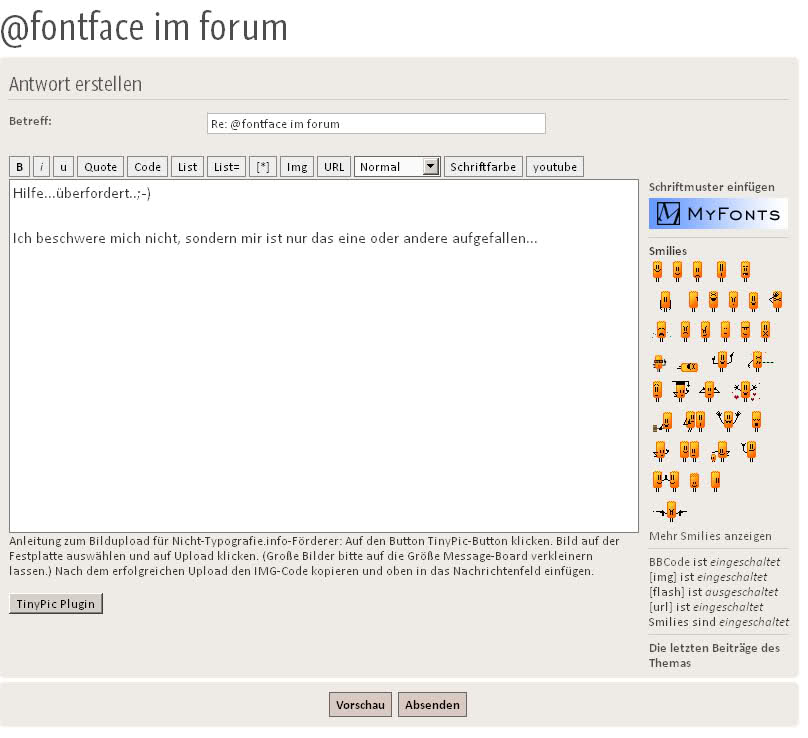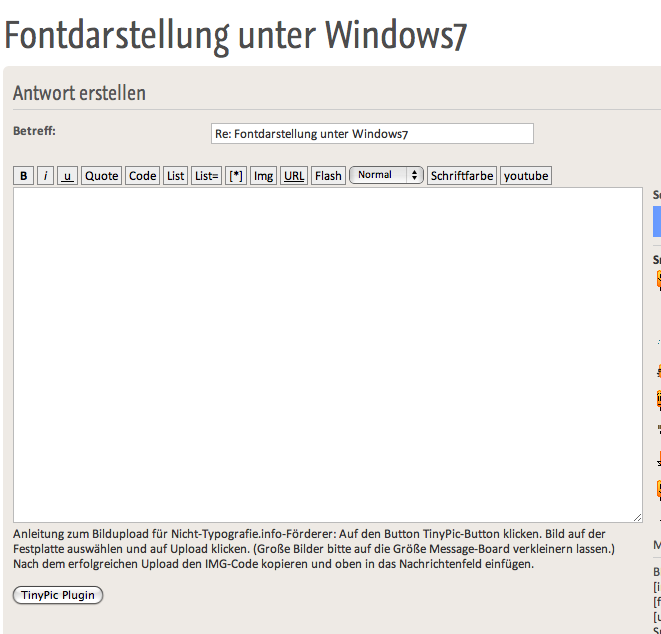
Fontdarstellung unter Windows7
Abgetrennte Diskussion von "@font-face im Forum"
Wenn ich meine unwissentliche Meinung abgeben dürfte (aber nicht hauen..;-) )
Das Problem der Darstellung ist mir auch schon aufgefallen, besonders im Eingabe-Editor.
Das ganze sieht aus wie bei Win7 mit eingeschaltetem ClearType (welches dort noch schlimmer ist als unter XP) und was auch der Grund für mich war, Win 7 erst mal nicht zu benutzen, da mir das Lesen mit solchen Buchstaben auf die Dauer zu anstrengend ist (ich merke wirklich dabei einen Unterschied zwischen XP und Win 7).
Da frage ich mich doch gleich, warum das als solch eine Errungenschafft angesehen wird, wenn sich eine Menge User im Netz darüber beschweren?
Was ich damit sagen will: Wenn jemand Win 7 hat, darf er sich nicht darüber wundern, dass die Schrift so ausschaut - nur ohne ClearType sieht es nur noch pixelig aus - warum gibt es nicht wie bei XP die Funktion "normal"?
Btw: Eine andere Frage, wo ich gerade die Fachleite hier habe: Ich weiß dass die Frage fast eienr Blasphemie gleich kommt, aber benutzt zufällig jemand heir Win 7 in Verbindung mit Photoshop, Illustrator und anderen Programmen und kann mir sagen wir ob die Schrift in den Programmen genauso ausschaut wie von Win 7 selber? Also genau so unscharf an den Rändern?
Hilfe...überfordert..;-)
Ich beschwere mich nicht, sondern mir ist nur das eine oder andere aufgefallen...
So schaut das ganze bei mir unter Win XP und FF aus:
Was ich jetz nur sagen woltle ist, dass Win 7 die Schrift generell schlchte darstellt (sieht man auch im FF):
Win XP:
Win 7:
Nicht das jemand denkt, wir schlecht die Schrift hier an manchen Stellen ist, und es liegt doch an Win 7...
Möglich, dass die Cleartype-Standardmethode von XP mit deinem Display besser funktioniert hat als die von Win7 - deine Screenshots deuten darauf hin. Cleartype-Tuner hilft.
Darstellung von Schrift in Photoshop, Illustrator, Indesign, ...: nein, diese Programme stellen Schrift auf ihre Weise mit einer eigenen Rasterungsmethode dar - möglichst Print-nahe, während das System die Schriften möglichst Bildschirm-optimiert darstellt (so der Microsoft-Ansatz).
Dann schmeiß mal den ClearType Tuner an – das sieht wirklich gruselig aus und hat mit dem eigentlichen Thema hier (@font-face bei den Überschriften im Forum) nur indirekt zu tun.
Ichdachte halt dass es damit zu tun haben könnte, da auf der ersten Seite auch über die Schaltflächen geredet wurde, und da tritt ja das gleiche Problem auf...
Den ClearType-Tuner hatte ich damals ausprobiert, aber hat - ehrlich gesagt - nicht das gleiche Bild gebracht wie bei XP. Deswegen bin ich auch wieder zurück auf XP und die Win 7-DVD liegt jetzt hier rum...
@Sebastian
Ich habe es an 4 Monitoren und einem Notebook ausprobiert, und zwei der Monitore sind nicht mal ein halbes Jahr alte Samsung-Monitore...sicherlich nicht das Beste, aber auch nicht das schlechteste...und bei vielen werden ja noch schlechtere, preiwertere Monitore benutzt, also sollte doch da schon die Schrift vernünftig ausschauen...oder bin ich zu verwöhnt?
Nicht verwöhnt – du bist die 90er-Jahre-Bitmap-Darstellung gewöhnt.
Das mag sein, aber warum ist dann dabei das Lesen für mich bei der neuen "Darstellung" wesentlich anstrengender?
Das wäre ja nicht so schlimm, wenn es an den Enden nur "unscharf" wäre, aber da kommen oft auch Farbpixel mit rein...und das irritiert...auch dass Buchstaben teilweise unterschiedliche breite haben, je nach dem mit welchen Buchstaben sie zusammen stehen:
genau deshalb habe ich anmeinem röhrenmonitor cleartype aus.
hier am 24'' display aber möchte ich es nicht missen, alles top.
vielleicht fährst du ja in einer falschen bildschirmauflösung?
genau deshalb habe ich anmeinem röhrenmonitor cleartype aus.
hier am 24'' display aber möchte ich es nicht missen, alles top.
vielleicht fährst du ja in einer falschen bildschirmauflösung?
Ne, bei beiden die richtige Auflösung, die gleiche wie auch unter XP, und da sieht es auch scharf aus. Auch mit der Bildwiederholung habe ich rumprobiert, keinen Unterschied...
Bei deinem XP-Screenshot ist ClearType ja auch aus, bei dem von Windows 7 nicht. Klar, dass das völlig anders aussieht.
Aber bei XP habe ich bei der Schriftenglättung die Wahl zwischen ausschalten, Standard und ClearType, bei dem Bild stand es auf "Standard", ClearType war also zwar ausgeschaltet aber die Kantenglättung aktiv.. Bei Win 7 habe ich nur die möglichkeit ausschalten (und eine heftig pixelige Schrift) und ClearType - für mich also die Wahl zwischen Pest und Cholera...
Wo siehst Du denn bei dem Bild einen Buntstich? Ich seh da nur Graustufen an den Kanten.
Es gibt ein kleines Programm namens "ClearType Tuning" (Systemsteuerung) von MS für XP und Vista (bei 7 ists mit eingebaut).
Damit kann man Cleartype an seinen Monitor anpassen. Schon merkwürdig das es nicht einfach als Update oder im Servicepack nachgeliefert wurde.